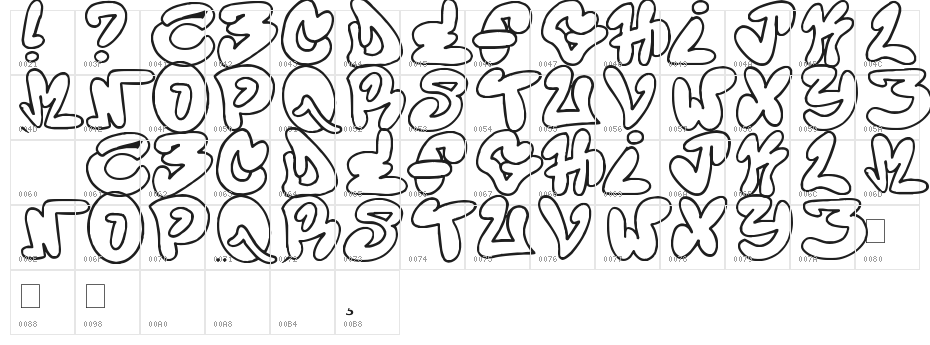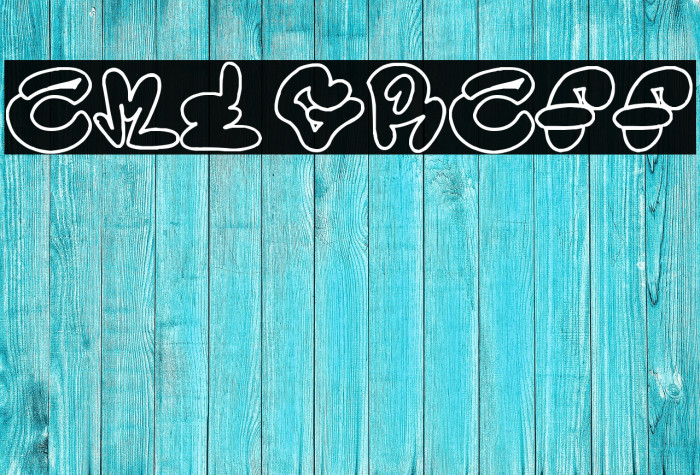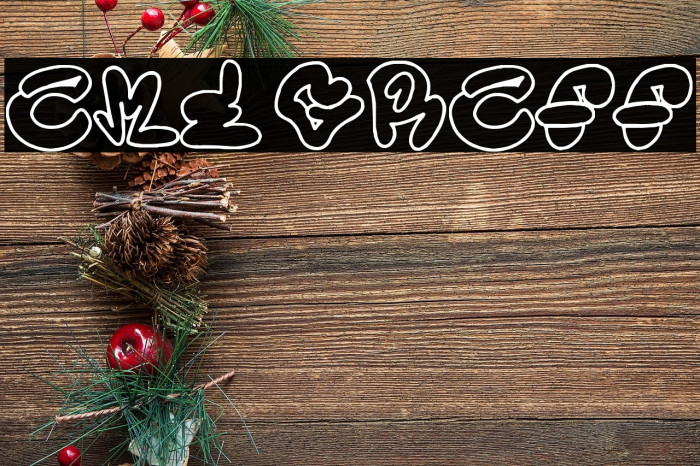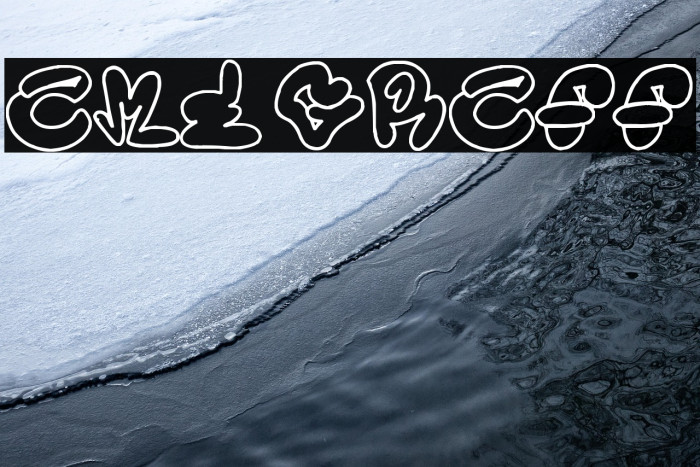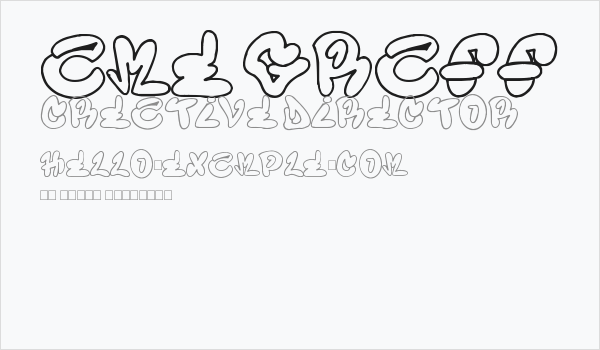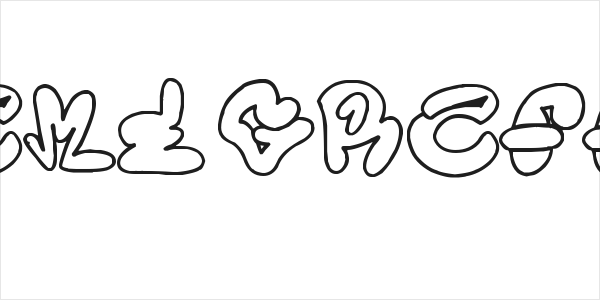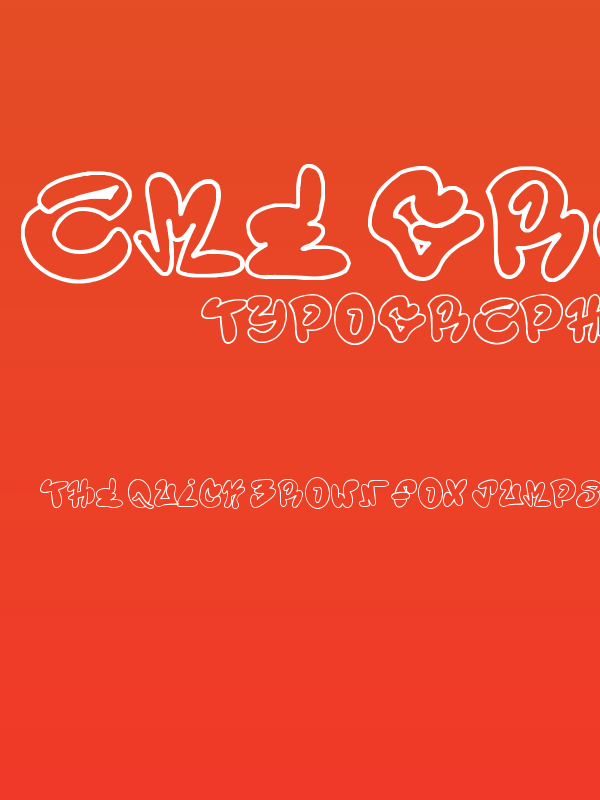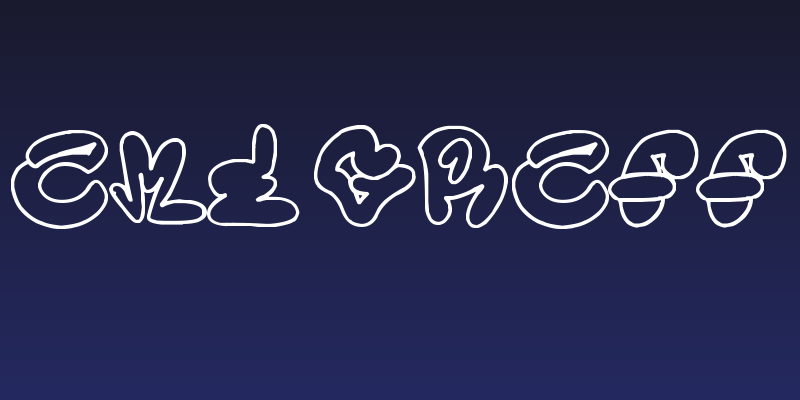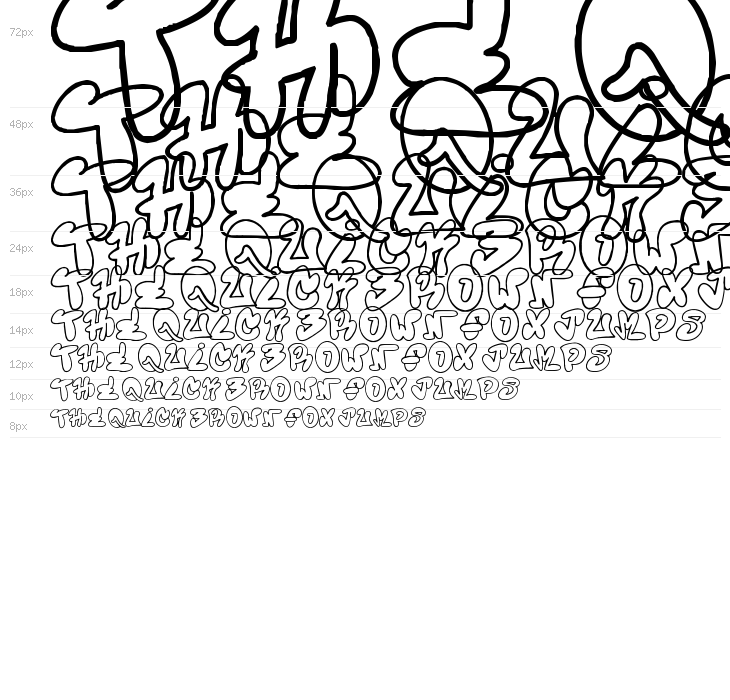
ame graff Font
| Estilo general | Urban, Artistic, Playful |
| Proyectos propuestos | Perfect for street art designs, urban-themed posters, music album covers, and creative branding projects. |